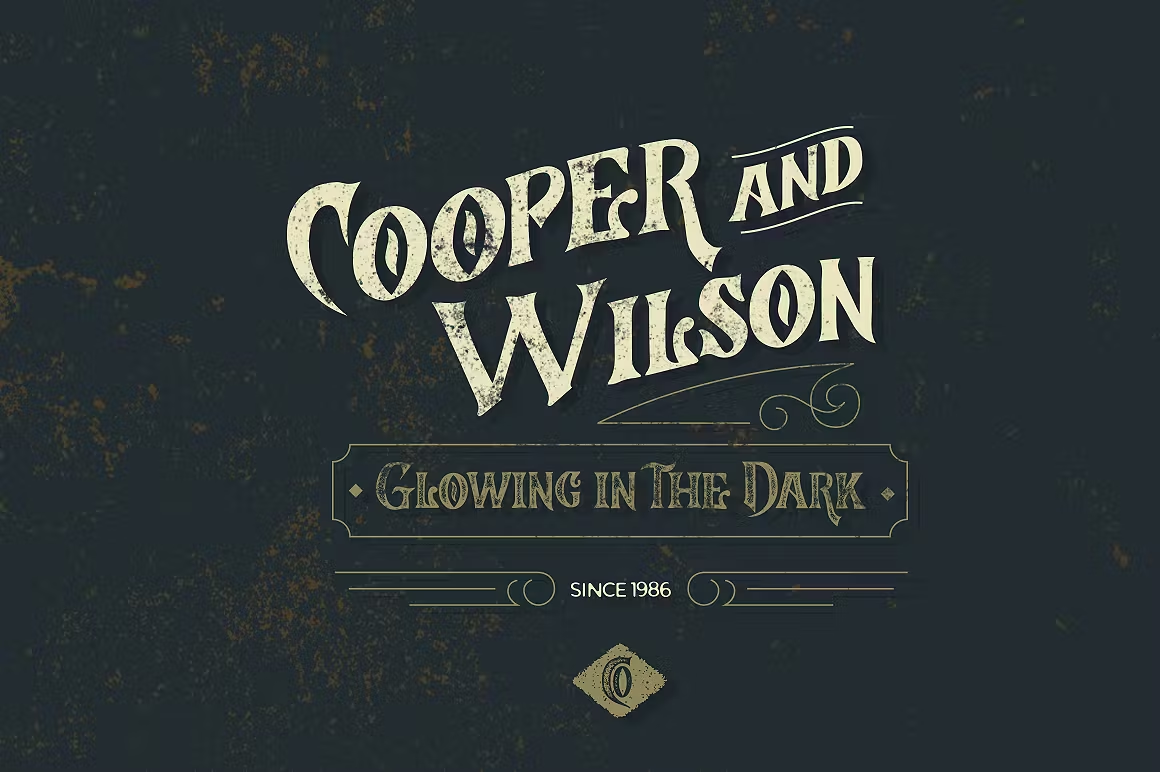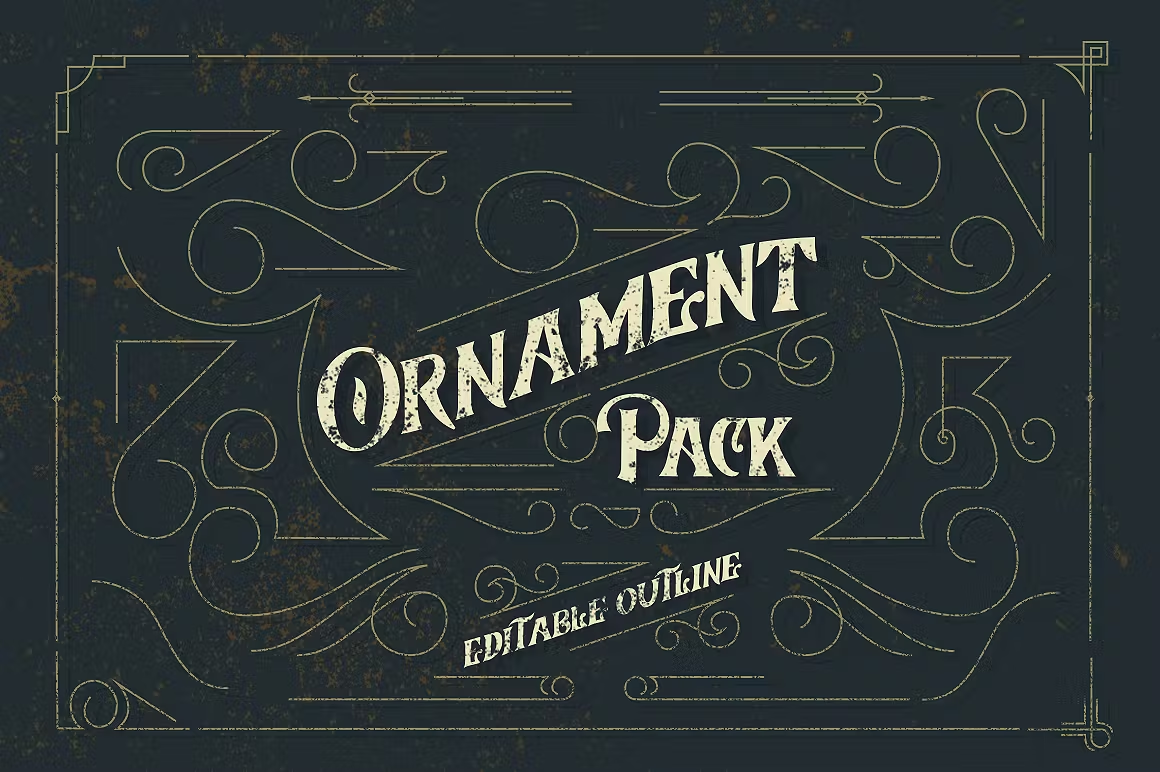
Brighton Smith Typeface
Présentation de la police Brighton & Smith. Créez à partir d’un style dessiné à la main (disponible avec 2 styles d’épaisseur), inspiré du vintage, costume pour en-tête, logo, marque, vêtements, affiche, citation comprenant un pack d’ornements pour subtiliser et décorer avec ce type. Bon pour le thème vintage.
Suppléants
ligature
Numérotation à l’ancienne
ponctuel